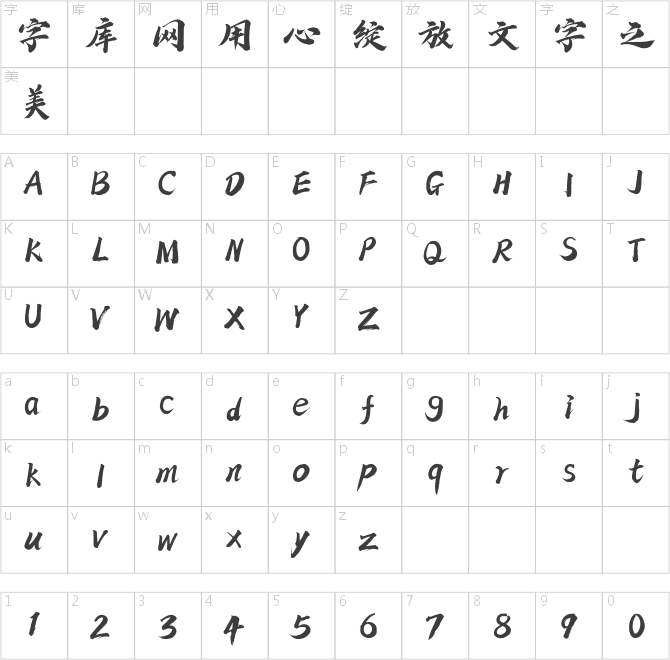
方正字跡-仝斌飄逸體 詳情頁
方正字跡-仝斌飄逸體,作者仝斌從事平面設計行業(yè),多年的實戰(zhàn)經(jīng)驗,讓他對字體的結(jié)構(gòu),和筆畫節(jié)奏有很深的理解。加之對生活的感悟和自身的書寫習慣,字體在力與美之間尋找微妙的平衡,形成獨特的剛?cè)岵拿栏校瑐€性鮮明,自成一體。適合于電影海報、包裝、品牌名稱、戶外廣告標題等。